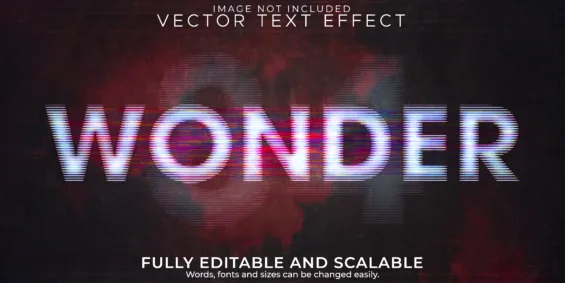
Oggi vediamo com’è e come utilizzare uno degli strumenti più potenti del visual design contemporaneo. La tipografia cinematica comprende lettere che entrano in scena e si trasformano, accompagnando lo sguardo come farebbe una colonna sonora. Un movimento che si trasforma in narrazione e nel contesto del web design e della grafica digitale, questo approccio tipografico sta diventando sempre più centrale, soprattutto in un’epoca in cui l’attenzione dell’utente è breve e il contenuto deve colpire in pochi secondi.
Cos’è (davvero) la tipografia cinematica?
C’è tipografia e tipografia. Quella cinematica va oltre l’idea di testo animato. Qui il movimento non è decorazione, ma linguaggio. Le parole non compaiono semplicemente sullo schermo, ma vengono introdotte con un ritmo preciso, spesso ispirato al cinema, ai trailer, alle sequenze di apertura delle serie TV. Ogni animazione ha un tempo, una pausa, un’accelerazione che contribuisce a costruire un’emozione.
Nel design digitale, questo tipo di tipografia viene utilizzato per guidare la lettura, creare attesa o rafforzare un messaggio chiave. È un modo per dare voce al testo, rendendolo protagonista e non semplice supporto visivo.
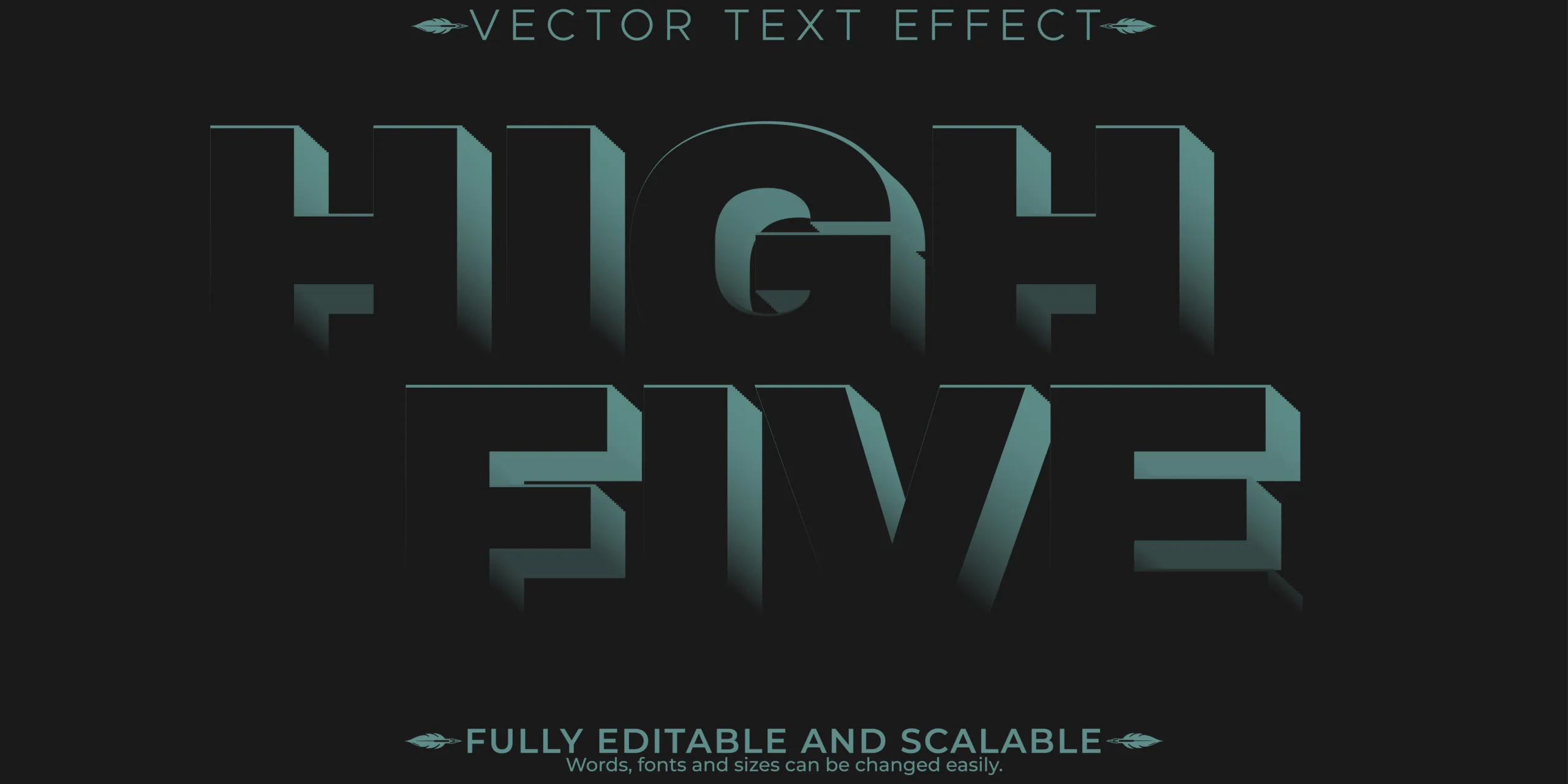
Uno strumento che funziona perché sfrutta un principio fondamentale, ovvero quello per cui l’occhio umano è naturalmente attratto dal movimento. Permette, quindi, di mantenere l’attenzione senza sovraccaricare l’interfaccia.
Il movimento deve però essere coerente con il messaggio. Una tipografia che entra lentamente in scena comunica solidità e riflessione, mentre testi che appaiono con tagli netti e rapidi suggeriscono energia, urgenza o innovazione. La scelta del ritmo è una scelta narrativa, non tecnica.
Storytelling digitale
La tipografia cinematica serve dunque a creare narrazione e viene utilizzata per tutto ciò che è Storytelling. Nei siti one page, nell’Ending page o nei progetti editoriali digitali, il testo animato fa da guida nell’accompagnare l’utente lungo la storia.
Le parole possono anticipare un contenuto, sottolineare un passaggio o chiudere una sezione con un effetto memorabile. Ecco quindi che l’elemento tipografico assume un ruolo simile a quello del montaggio cinematografico, dove le pause contano quanto le animazioni e il silenzio visivo tra una parola e l’altra diventa parte integrante del racconto.
Detto questo, dobbiamo anche precisare che non tutti i font funzionano bene con questo tipo di tipografia. Alcuni caratteri sono progettati per restare fermi, altri invece reagiscono meglio al movimento. Font con geometrie pulite, pesi variabili e buona leggibilità anche in transizione sono ideali per animazioni fluide e professionali.
Ciò che è fondamentale è la coerenza, perché un animazione sofisticata su un font inadatto può risultare artificiale o confusa. Al contrario, una tipografia ben scelta, anche con movimenti minimi, può trasmettere eleganza e controllo. Nel design cinematico, spesso meno è più.
Tipografia cinematica nel web design di oggi
A questo punto non ci resta che contestualizzare questo tipo di tipografia. La tipografia cinematica oggi viene integrata nei linguaggi del web grazie a nuove tecnologie e ad animazioni basate su scroll e testo che reagisce al comportamento dell’utente.
L’obiettivo è sempre lo stesso: creare un’esperienza dinamica di immersiva. Ecco perché questo approccio è particolarmente efficace soprattutto nei portfolio creativi e nei progetti editoriali digitali dove l’impatto visivo e parte del valore del contenuto.
I trend attuali ci dicono che le animazioni più gettonate sono quelle naturali, meno meccaniche, ispirate al movimento reale al cinema d’autore. Perché? Perché si vuole coinvolgere l’utente più che stupirlo.
Quando usarla e quando evitarla
Stiamo parlando di uno strumento potente che però va usato con consapevolezza. La tipografia cinematica funziona davvero quando serve a rafforzare un messaggio o a guidare l’esperienza utente, ma diventa un effetto fine a se stesso in tanti altri casi come ad esempio nei contesti informativi e molto testuali.
La cosa fondamentale da tenere di conto è lo scopo che l’animazione ha all’interno del design di un sito web. Sì il contesto ci permette o ci richiede una narrazione visiva intensa, allora la tipografia cinematica può contribuire a creare un’esperienza coerente, memorabile e profondamente contemporanea, altrimenti è solo qualcosa che può compromettere la leggibilità e affaticare l’utente.